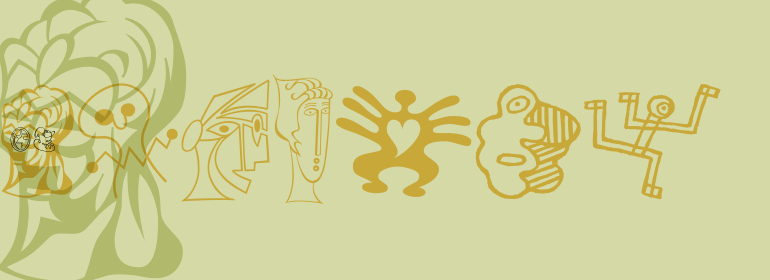
Moderns™
Moderns™,这款字体结构工整、笔画清晰,兼顾美观与易读性,适用于标题、正文、海报、包装、LOGO 等多种场景。字形优雅稳定,风格百搭耐看,适配日常排版与创意设计,让文字呈现更舒适、更具质感。Moderns™一笔一画,皆是细节,以均衡的比例、流畅的线条打造舒适视觉体验,字形端正大气,风格简约现代。无论是商业设计、品牌宣传还是日常排版,都能轻松驾驭,让文字更有格调与力量。Moderns™字体下载。
字体品牌: ITC(Monotype) 设计师:Sagorski,David 字体分类:符号 字体属性:外文 字符集:Unicode 发布时间: 2018